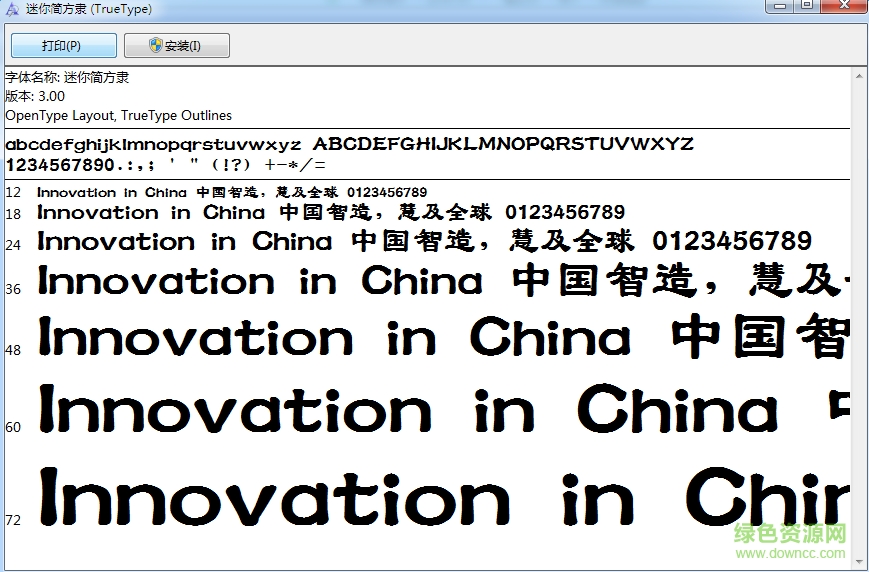
迷你簡方隸是一款根據(jù)隸書制作的字體,字體結(jié)體扁平、工整、精巧,撇、捺、點(diǎn)等畫美化為向上挑起,輕重頓挫富有變化,具有書法藝術(shù)美,喜歡這款字體的朋友歡迎來綠色資源網(wǎng)下載體驗(yàn)!
迷你簡方隸字體是一款具有古典美感的字體,看起來非常的大氣,就像是用毛筆寫出來的一樣